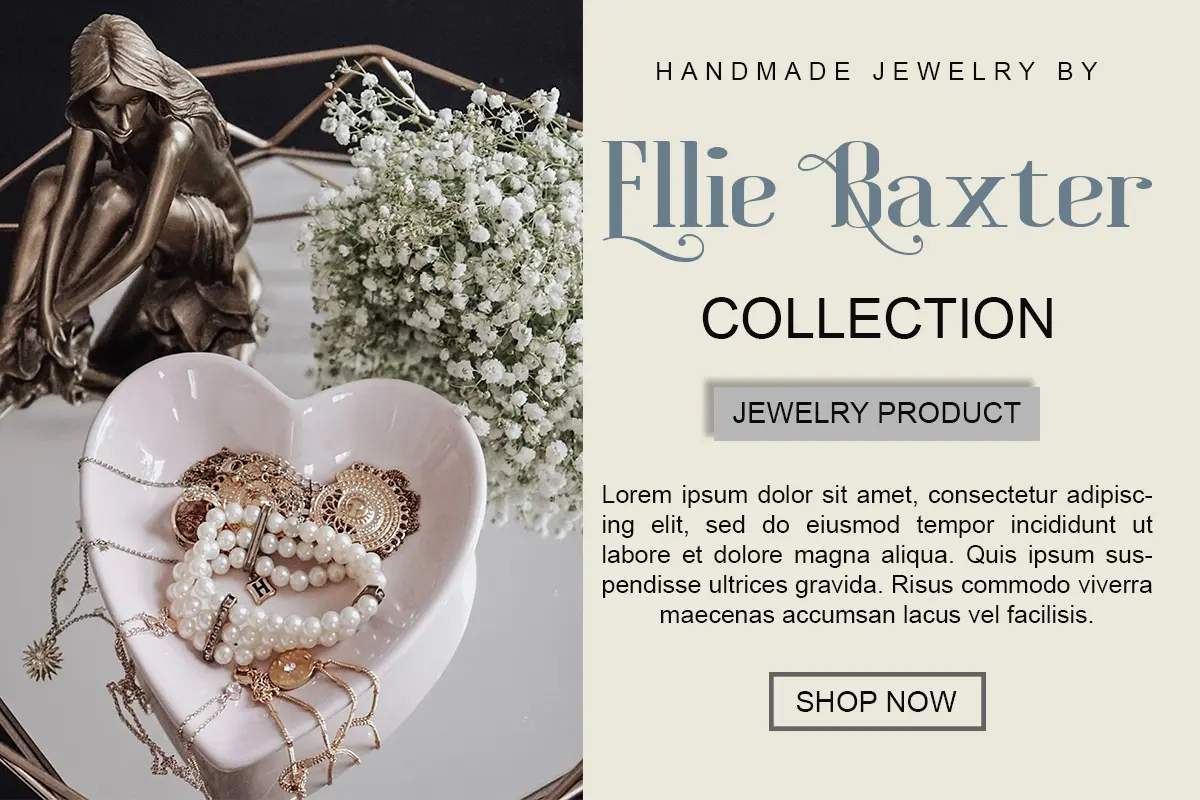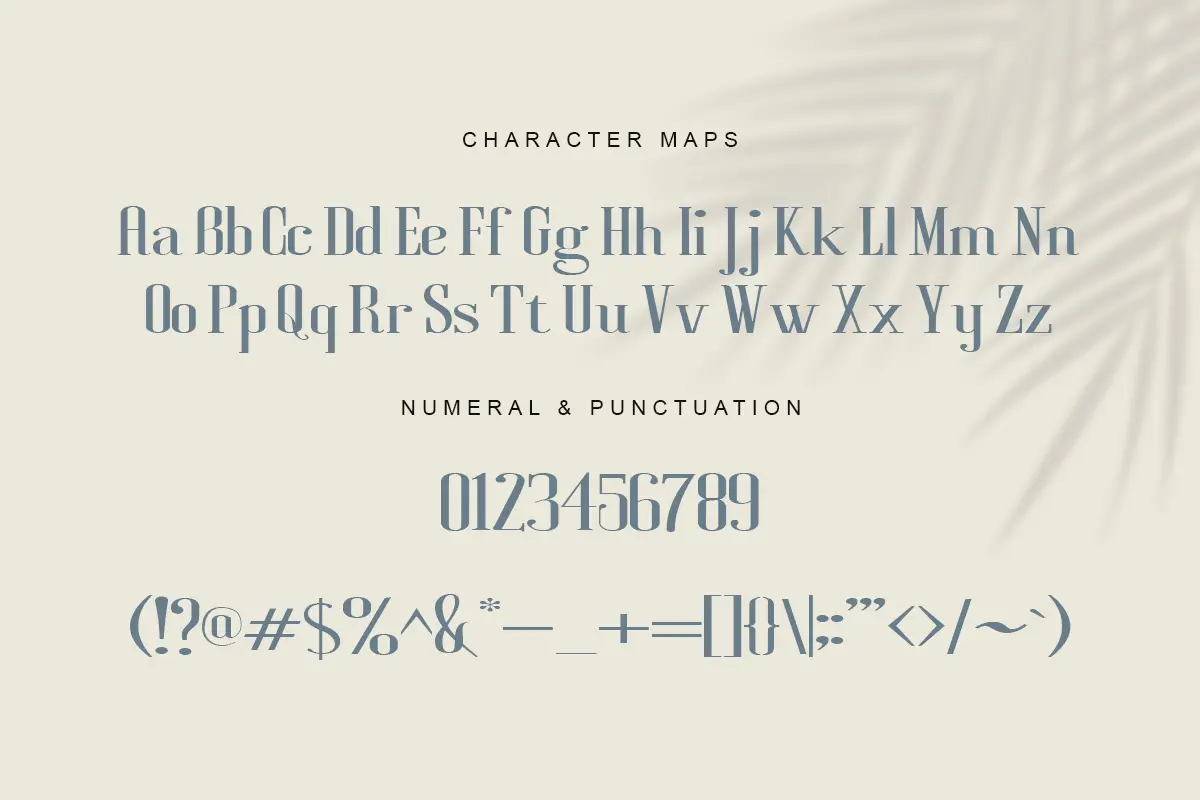
فونت سریف مدرن و شیک
فونت Sannia یک تایپفیس سریف مدرن و شیک است که برای پروژههای خلاقانه طراحی شده. این فونت با استایلهای متنوع و قابلیت چندزبانه، جلوهای زیبا و حرفهای به کارهای شما میبخشد. همچنین به دلیل PUA Encoded بودن، دسترسی به تمام گلیفها و سوئشها بسیار آسان است.
⭐ ویژگیهای محصول
- فونت سریف مدرن و کلاسیک
- مناسب برای لوگو برندها، دعوتنامهها، کارتهای تبریک و پروژههای خلاقانه
- دارای ویژگیهای چندزبانه
- شامل استایلهای متنوع برای انعطاف بیشتر در طراحی
- PUA Encoded برای دسترسی راحت به گلیفها و سوئشها
🎯 موارد استفاده
- طراحی لوگوهای برندینگ لوکس و مدرن
- ساخت دعوتنامههای رسمی و کارتهای تبریک
- استفاده در پروژههای چاپی و دیجیتال
- افزودن جلوه زیبا و حرفهای به طراحیهای گرافیکی